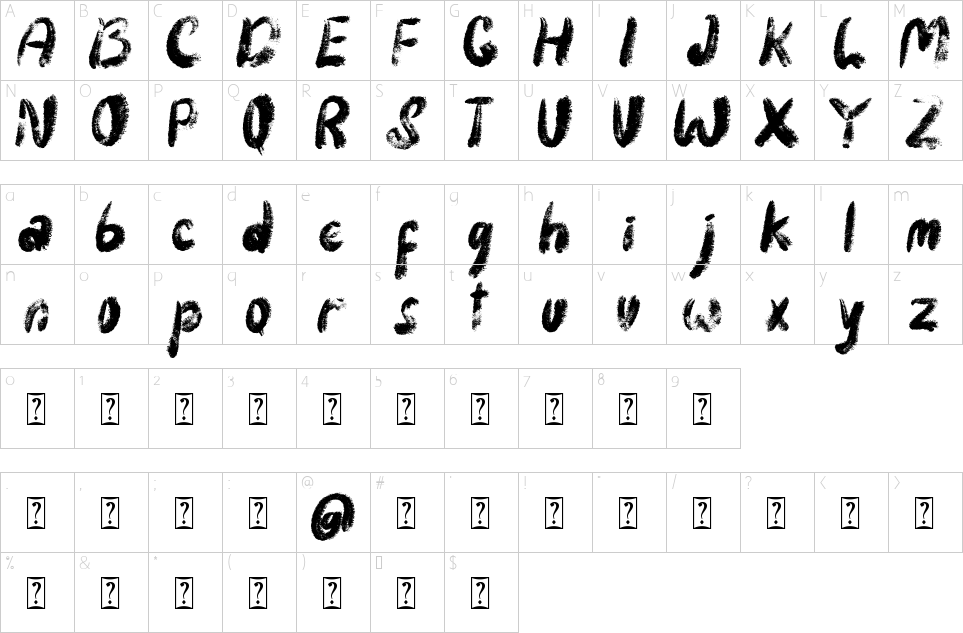
A Zombi Predator é uma nova fonte que combina elementos estilizados com aspectos sobrenaturais em seu design, resultando num visual impactante e único. Desenvolvida pelo designer Yoga Letter, esta font oferece um conjunto de caracteres dinâmico capaz de se adaptar a diversos usos. Suas formas desenhadas em zumbis e predadores vivem dentro do mesmo universo, criando uma atmosfera futurista e sombria. Compreendendo sua versão para Windows e Mac, esta font é um complemento perfeito para projetos de design gráfico que valorizam estilos distantes e imaginativos. Seja você um designer digital ou criação de material em 2D, a Zombi Predator pode ajudá-lo a inovar em seus trabalhos criando uma identidade visual única e impressionante. Há setecentas vezes que esta font foi baixada, confirmando seu valor como opção gratuita para projetos que exigem um aspecto único e sofisticado.